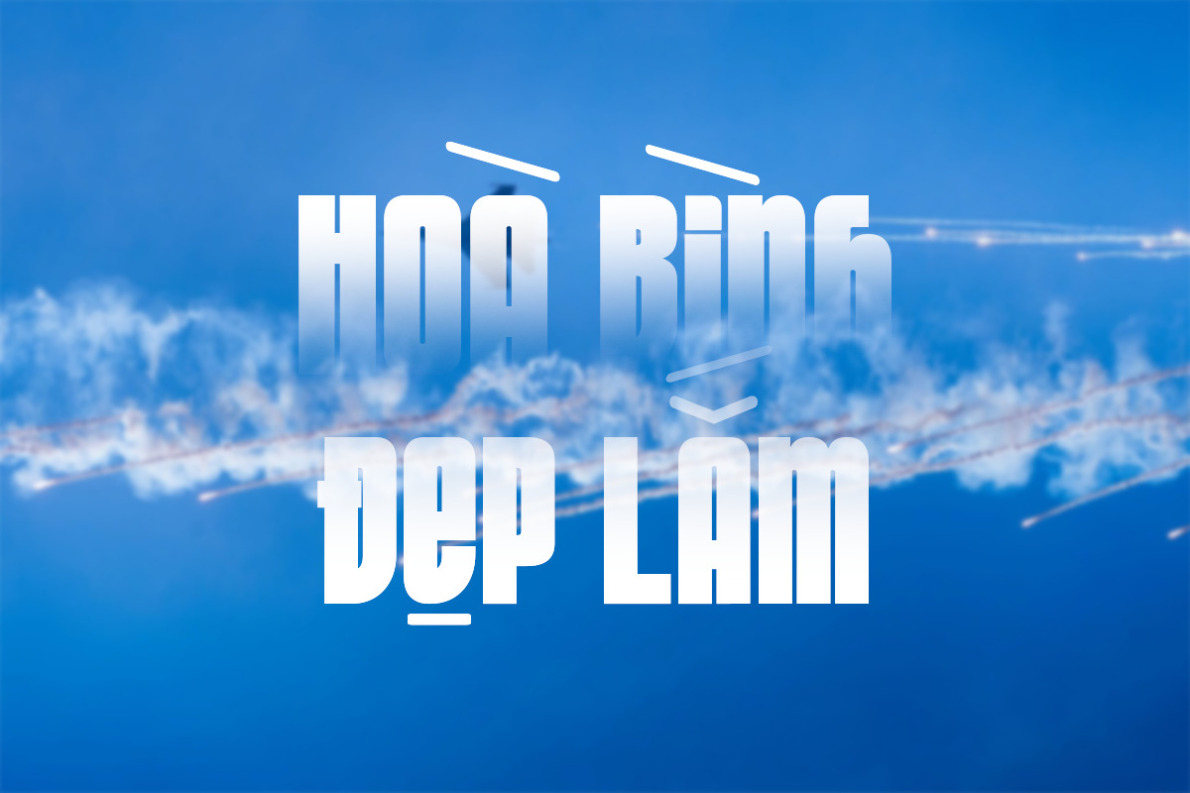
Font Việt hóa MJ Moregans – Font Vintage Không Chân Đậm Nét
Giới thiệu Font MJ Moregans Việt hóa
MJ Moregans là một kiểu chữ sans serif không chân mang phong cách cổ điển vintage, với các đường nét dày dặn, chắc chắn và đậm đà. Font gợi lên cảm giác hoài niệm, rất thích hợp cho những thiết kế cần yếu tố lịch sử hoặc tái hiện không khí xưa cũ.
Phiên bản Việt hóa của MJ Moregans đã được tinh chỉnh tỉ mỉ để hỗ trợ đầy đủ bộ dấu tiếng Việt, giúp font trở nên hoàn thiện cho nhiều ứng dụng thực tế. Với đặc trưng đậm nét và mang tính cổ điển, font này lý tưởng cho thiết kế tiêu đề nổi bật, poster quảng cáo về lịch sử, banner cổ động hoặc các ấn phẩm kỷ niệm truyền thống.
Điểm nổi bật của MJ Moregans Việt hóa
Việt hóa đầy đủ dấu tiếng Việt.
Thiết kế sans serif cổ điển, đậm nét.
Phù hợp cho tiêu đề, poster quảng cáo lịch sử, banner cổ động.
Phong cách vintage hoài cổ mạnh mẽ.